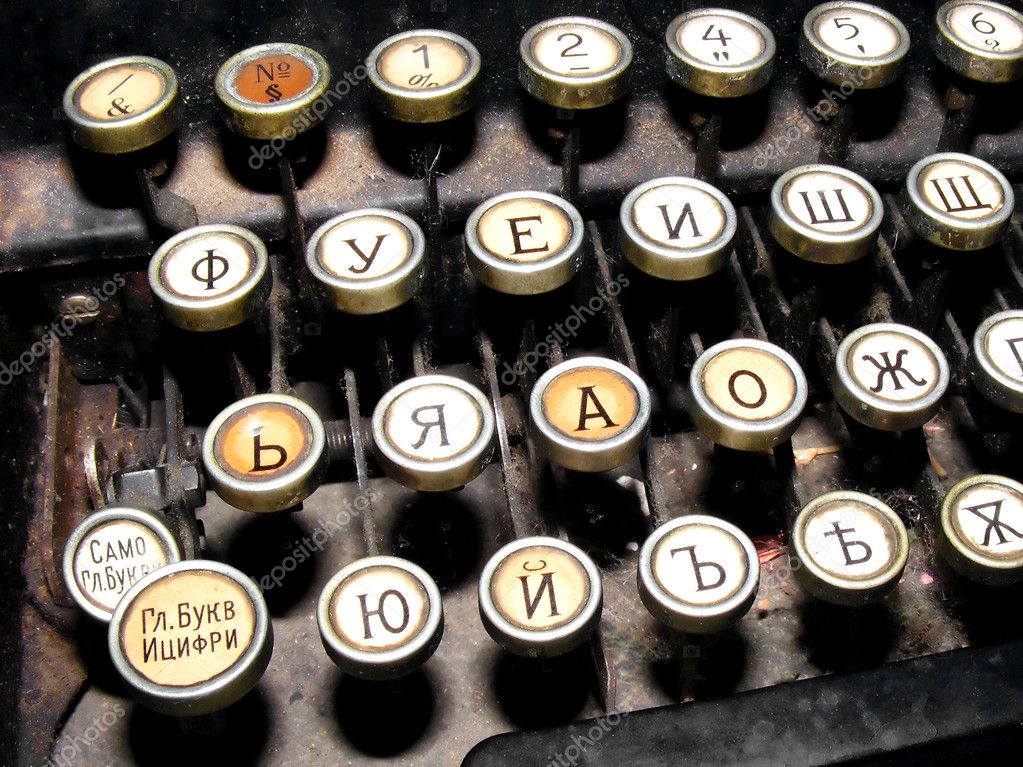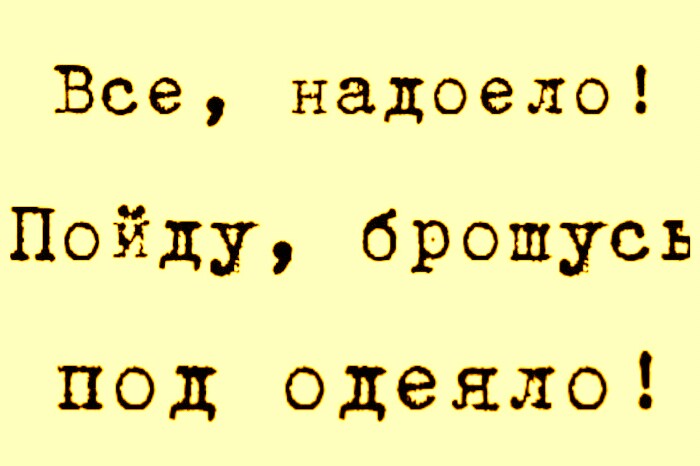
Typographic fonts old typewriter, close-up
Дорожная пишущая машинка
Вот шрифт, основанный на старой датской пишущей машинке, произведенной в западной Германии. Дизайнер шрифта дал ему плоскую базовую линию, но разница в высоте и весе букв придает ему аутентичный вид.
CarbonType
CarbonType был отсканирован непосредственно со старой пишущей машинки Samsonite. Если вам нужна аутентичность, вы найдете ее здесь. Дизайнер сказал, что на машине не было номера один, поэтому вместо него пришлось использовать строчную букву L.